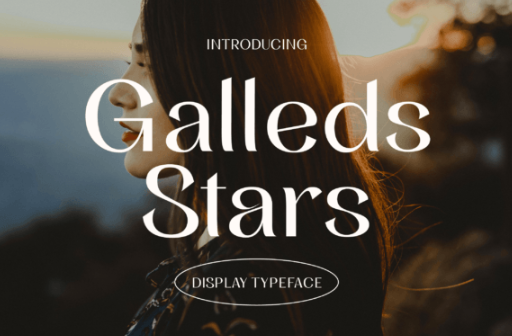
Galleds Stars Display Typeface - это один шрифт с минималистичным, но выделяющимся стилем для любых работ, от названий фильмов, обложек музыкальных альбомов, журналов, рекламы косметики и даже свадебных приглашений.
Минималистский дизайн шрифта, который пользуется успехом у профессиональных дизайнеров по всему миру.
- Дисплейный шрифт Galleds Stars читается с гораздо большего расстояния, чем обычные шрифты - Элегантные формы букв создают ощущение роскоши
- Плавные изгибы для элегантной типографики